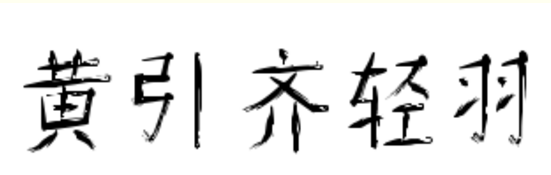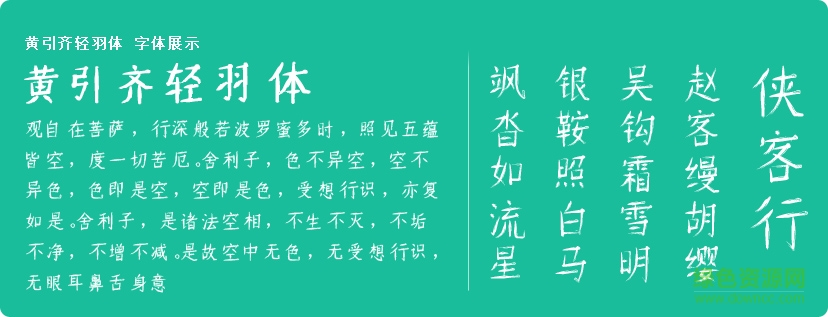
黃引齊輕羽是黃引齊字庫(kù)的獨(dú)特粗體書法字體,若明若隱的造型給人輕柔干凈的閱讀體驗(yàn),輕若羽毛纖秀怡人,綠色資源網(wǎng)誠(chéng)意推薦!
字體屬性黃引齊輕羽[書法]-粗體,字跡清秀簡(jiǎn)潔,廣泛適用于數(shù)字媒體、包裝設(shè)計(jì)、廣告設(shè)計(jì)、網(wǎng)頁(yè)設(shè)計(jì)等領(lǐng)域。